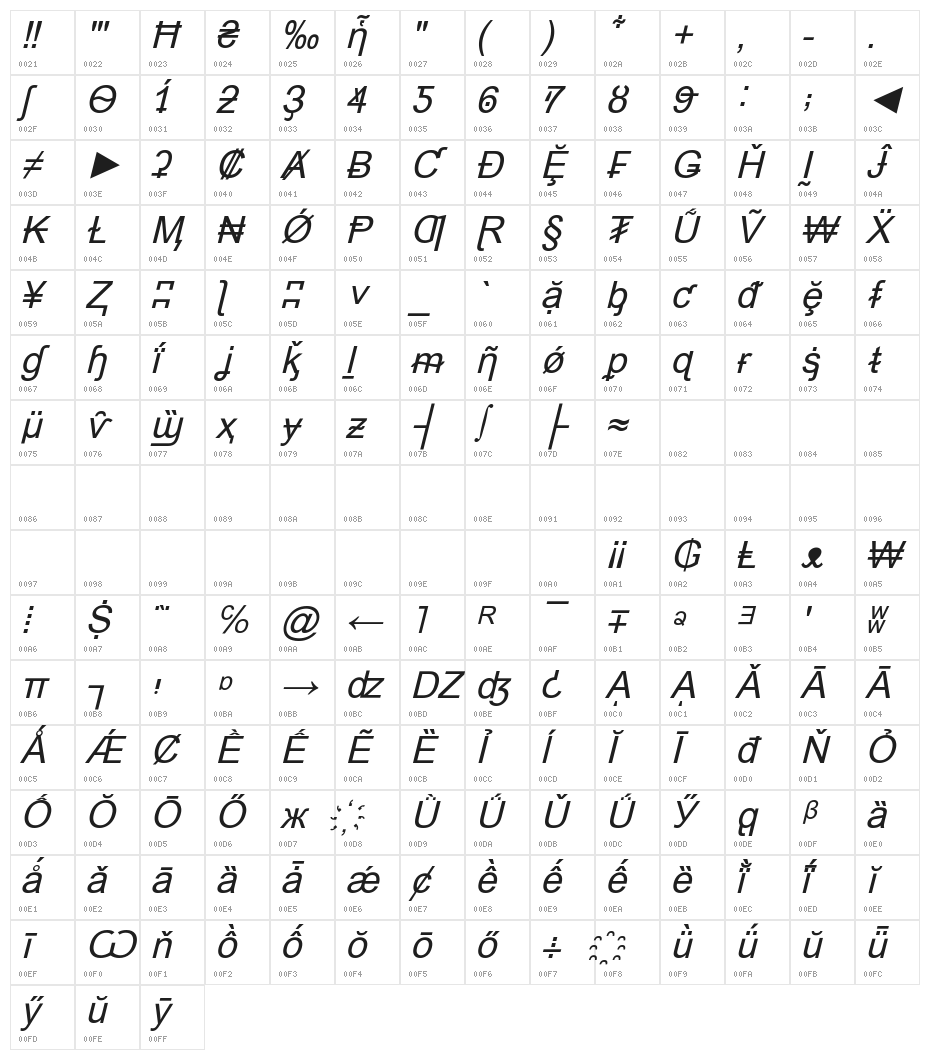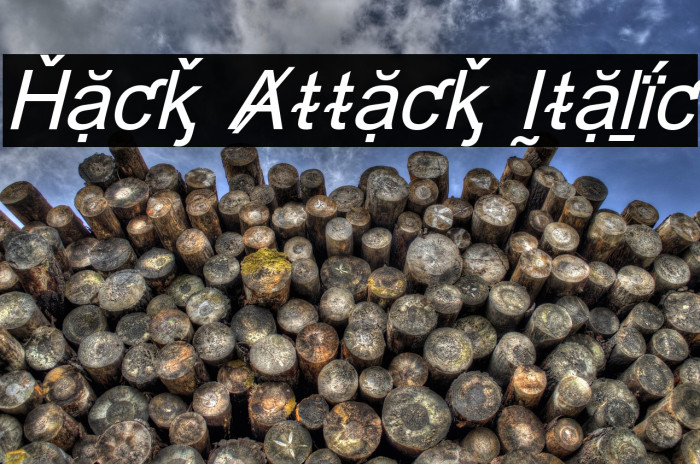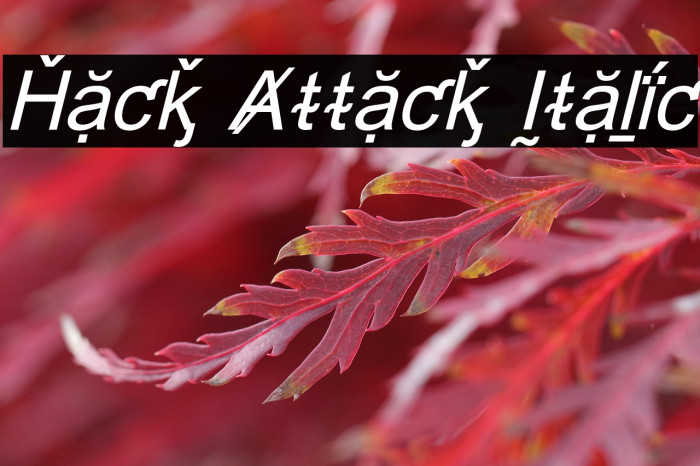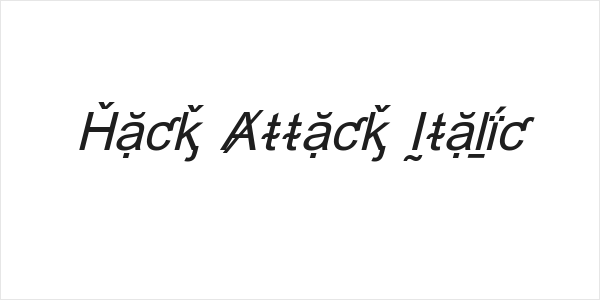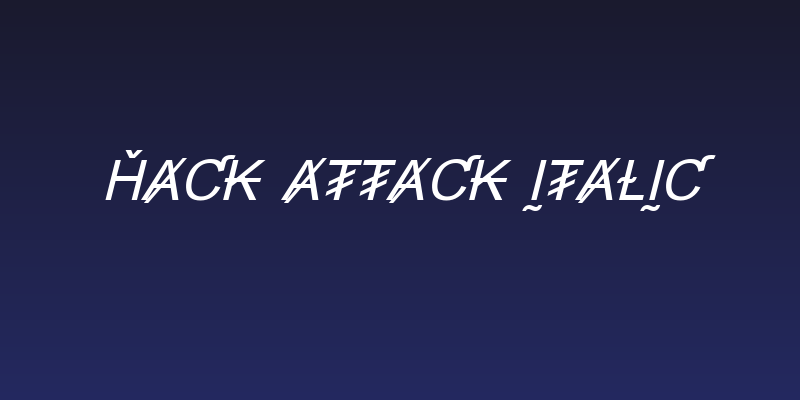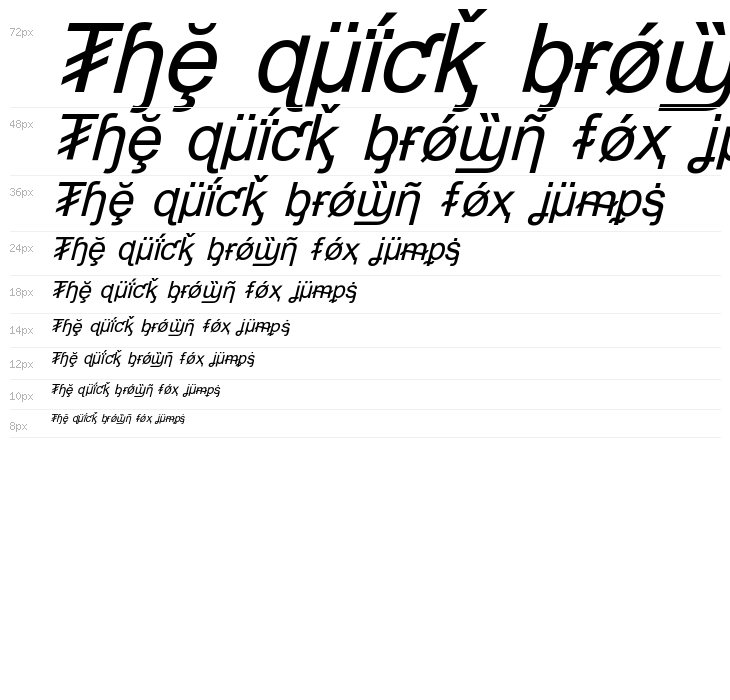
Hack Attack Italic Font
| Caz de utilizare | Headlines, Logos, Editorial design |
| Proiecte propuse | Ideal for branding, advertising, and editorial design projects that require a contemporary and energetic feel. |